说到字体,这可以说是我们在日常生活和工作当中最常用的东西,可能有一些人从来没有关注过自己的选择,而有些人则是经常跟字体打交道,比如说像广告设计或者是平面设计一类的行业,经常会跟字体打交道,毕竟不同字体会有不同的风格,表现出来的艺术美感也不一样,在艺术表现力上具有很大的差别。相信很多人也都听说过庞门正道字体,深受一些设计行业人的喜欢。那么庞门正道字体下载哪里比较好?是免费下载吗?
庞门正道字体下载之前需要先了解一下字体设计,庞门正道字体是字体设计师一起共同努力耗费了不少的心血才设计出了不同的字体。任何一种字体的字形以及编码都是要按照国家在语言文字的相关规定来进行设计的,这个主要是为了保证字库能符合相关的标准。
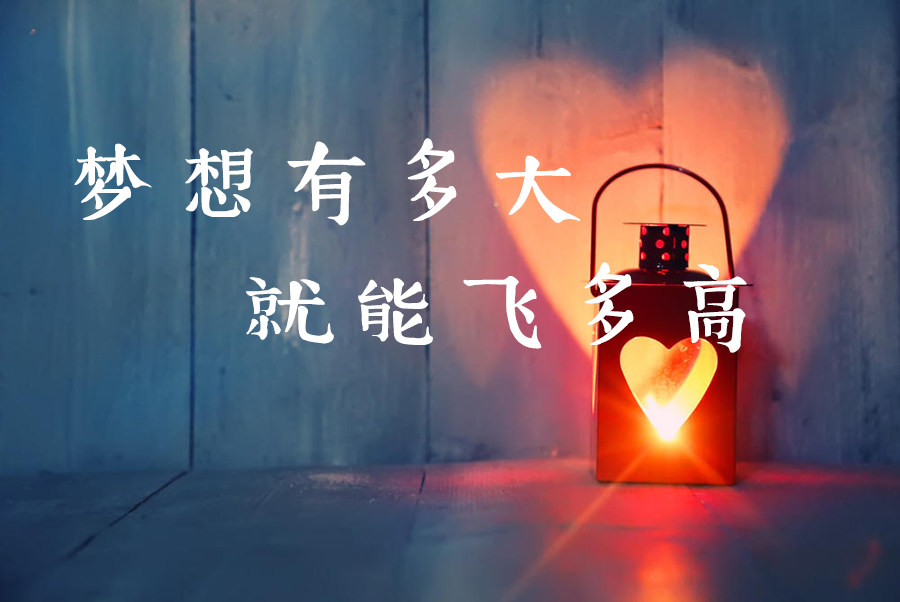
庞门正道字体下载的时候也需要考虑字体风格,现在的字体风格特别的多,有的给人的感觉比较柔美,有的则是比较挺拔,还有一些字体的风格就比较活泼有趣了,整个字体的造型都让人觉得特别的生动,感受到字体的活泼感,那种比较有节奏的韵律感是非常凸显的。不同的字体风格也会被运用与不同的领域,或者是不同的行业运用当中。比如说像,比较活泼有趣的字体风格,就更适合于儿童用品以及一些颇具时尚产品。